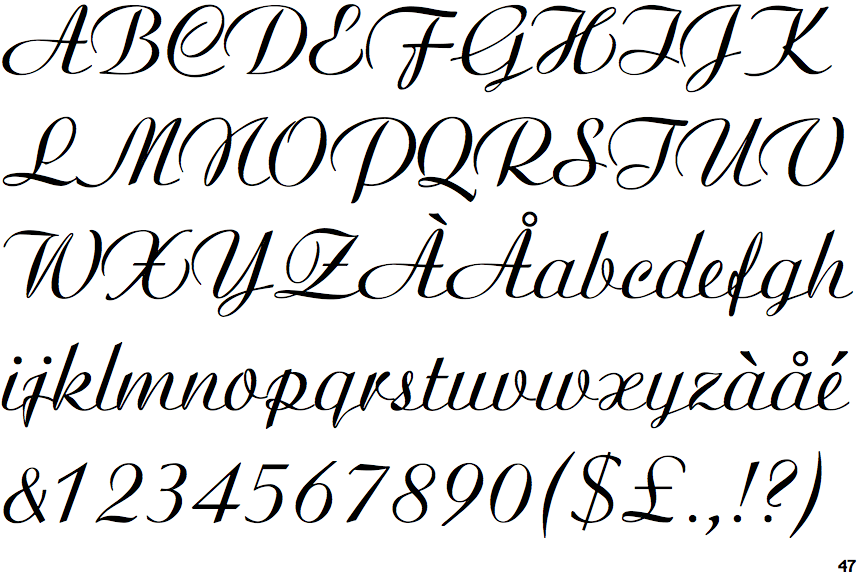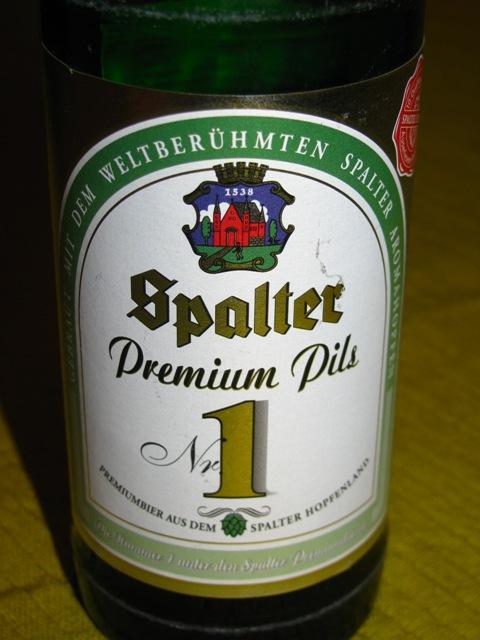
Spalter-Bier-Logo - Welche Schrift ist das?
Ich möchte ein Bierlabel in diesem Stil anfertigen - als Einladung für einen privaten Geburtstag.
Könnt ihr mir vielleicht weiterhelfen, welche Schriftarten hier verwendet wurden?
Beim Schriftzug "Spalter" nehme ich an, dass es eine altdeutsche / altenglische Font ist, habe ein paar FreeFonts gefunden (z.B. Offenbacher / Schwabacher) aber finde nicht den exakten Match.
"Premium Pils" ist irgendeine Schreibschrift, habe aber auch hier noch kein Pendant gefunden, welches mir zusagt.
Der gebogene Schriftzug im grünen Bereich dürfte wohl das einfachste sein ...
Bier-Markenlogos, egal wie sehr sie wie ein sauberer Font aussehen, sind sehr oft frei gezeichnet. (Fonts sind ja letztlich auch einzeln gezeichnete Buchstaben, die irgendwann irgendwer genau so selbst gezeichnet hat)
Vielleicht kann ich dir ja mit diesen Schriften helfen:
und für die Schreibschrift vielleicht so etwas:
die Schreibschrift ist eine sehr alte Bekannte.
Typeface:    Ariston
Designer:    Martin Wilke
Year:        1933
Publisher:    Berthold
Alternates:    Arioso SM (Star Office)
Die abgegebene Arioso SM wurde um 2000 rum mit Star-Office frei verteilt. Ich habe die Schrift noch aus den alten OS/2-Versionen gesichert. Die Frage nach dieser Schrift tauchte hier übrigens schon mal auf:
Ach ja! Die ist übrigens schon lange bei Corel dabei, und übrigens auch als Markenlogo auf meinem alten Rechenstab drauf, nur eben ohne n am Ende :-)
Da bin ich jetzt verwirrt. Unter welchen Namen? Die Ribbon 131 ist es ja nicht und was anderes habe ich da nicht gefunden. Identifont schweigt sich da auch aus und auf Myfonts.com ist gerade nix zu recherchieren ...